15 แบบอักษร Divi ที่ดีที่สุดที่ควรลองในปี 2024 (การจับคู่ยอดนิยมและเคล็ดลับระดับมืออาชีพ)
เผยแพร่แล้ว: 2024-02-01Divi เป็นเพื่อนที่ดีที่สุดของนักออกแบบเว็บไซต์ เครื่องมือสร้างเพจแบบภาพช่วยปรับปรุงกระบวนการออกแบบและมาพร้อมกับระบบนิเวศที่น่าประทับใจของผลิตภัณฑ์และบริการของ Divi รวมถึง Divi Cloud, Divi Teams, Divi AI และอีกมากมาย อย่างไรก็ตาม โดยไม่คำนึงถึงกระแสความนิยมเกี่ยวกับฟีเจอร์เหล่านี้ ในโลกของการออกแบบเว็บไซต์ การพิมพ์คือองค์ประกอบการออกแบบพื้นฐานที่ไม่สามารถละเลยได้ นั่นคือจุดที่คลังแบบอักษรขนาดมหึมาของ Divi (ต้องขอบคุณ Google Fonts Integration ของเรา) และตัวเลือกการจัดรูปแบบข้อความที่มีประสิทธิภาพเข้ามามีบทบาท
ในโพสต์นี้ เราจะเน้นแบบอักษรและชุดค่าผสม Divi ที่ดีที่สุดสิบห้าแบบเพื่อให้คุณลองใช้ในปีนี้ รวมถึงเคล็ดลับและแนวทางปฏิบัติที่ดีที่สุดสำหรับการใช้งานบนเว็บไซต์ Divi ของคุณ
เกี่ยวกับตัวเลือกการจัดรูปแบบแบบอักษรและข้อความ Divi
Divi นำเสนอตัวเลือกการจัดรูปแบบแบบอักษรและข้อความที่หลากหลาย ซึ่งช่วยให้คุณปรับแต่งรูปลักษณ์ของเนื้อหาของคุณได้ คุณสามารถปรับสไตล์ข้อความ เช่น ขนาด น้ำหนัก ความสูงของบรรทัด ระยะห่างระหว่างตัวอักษร และตระกูลแบบอักษรสำหรับองค์ประกอบข้อความบนเว็บไซต์ของคุณได้อย่างง่ายดาย
15 แบบอักษร Divi และการรวมแบบอักษรที่ดีที่สุด
การเข้าถึงรายการแบบอักษรมากกว่า 800 แบบและลองตัดสินใจว่าแบบอักษรใดที่เหมาะกับโปรเจ็กต์ของคุณอาจเป็นเรื่องที่น่ากังวล หวังว่ารายการนี้ (ตามลำดับตัวอักษร) จะช่วยคุณตัดเสียงรบกวนและตัดสินใจเลือกการออกแบบที่แข็งแกร่งได้
ฉันพยายามอย่างเต็มที่เพื่อเน้นแบบอักษรที่เราไม่เคยกล่าวถึงในบล็อกของเรามาก่อน ในโพสต์ของเรา 12 แบบอักษร Google ที่ดีที่สุดสำหรับ WordPress เราได้กล่าวถึงแบบอักษร Google ยอดนิยมมากมายที่มีแนวโน้มว่าจะแนะนำ แบบอักษร Google ที่ได้รับความนิยมมากที่สุดสำหรับเว็บไซต์ ได้แก่:
- Lato (นั่นคือแบบอักษรที่คุณกำลังอ่านอยู่ตอนนี้)
- เมอร์ริเวเธอร์
- Poppins (ดูการสาธิต)
- การแสดงเพลย์แฟร์
- มอนต์เซอร์รัต
- และอื่น ๆ.
รายการด้านล่างประกอบด้วยแบบอักษรยอดนิยมเพิ่มเติม (รวมถึงอัญมณีที่ซ่อนอยู่) ที่คุณสามารถลองใช้เมื่อออกแบบเว็บไซต์ Divi ของคุณ สิ่งเหล่านี้มีอยู่ใน Divi builder และหลาย ๆ ตัวก็รวมอยู่ในแพ็กเค้าโครง Divi ที่สร้างไว้ล่วงหน้าของเรามากกว่า 250 แพ็ก
แบบอักษร Divi ที่ดีที่สุดเรียงตามลำดับ
- อเลเกรยา ซานส์
- โดยเร็วที่สุด
- ขม
- ฟิร่า แซนส์
- ไอบีเอ็ม เพล็กซ์ โมโน
- อินเตอร์
- คณิต
- ลิเบอร์ แฟรงคลิน
- คนอ่านข่าว
- โนโตะ เซริฟ
- นูนิโต
- พีที แซนส์
- แบบสอบถาม
- ซ้ำ
- โวลกรณ์
1. อเลเกรย่า ซานส์
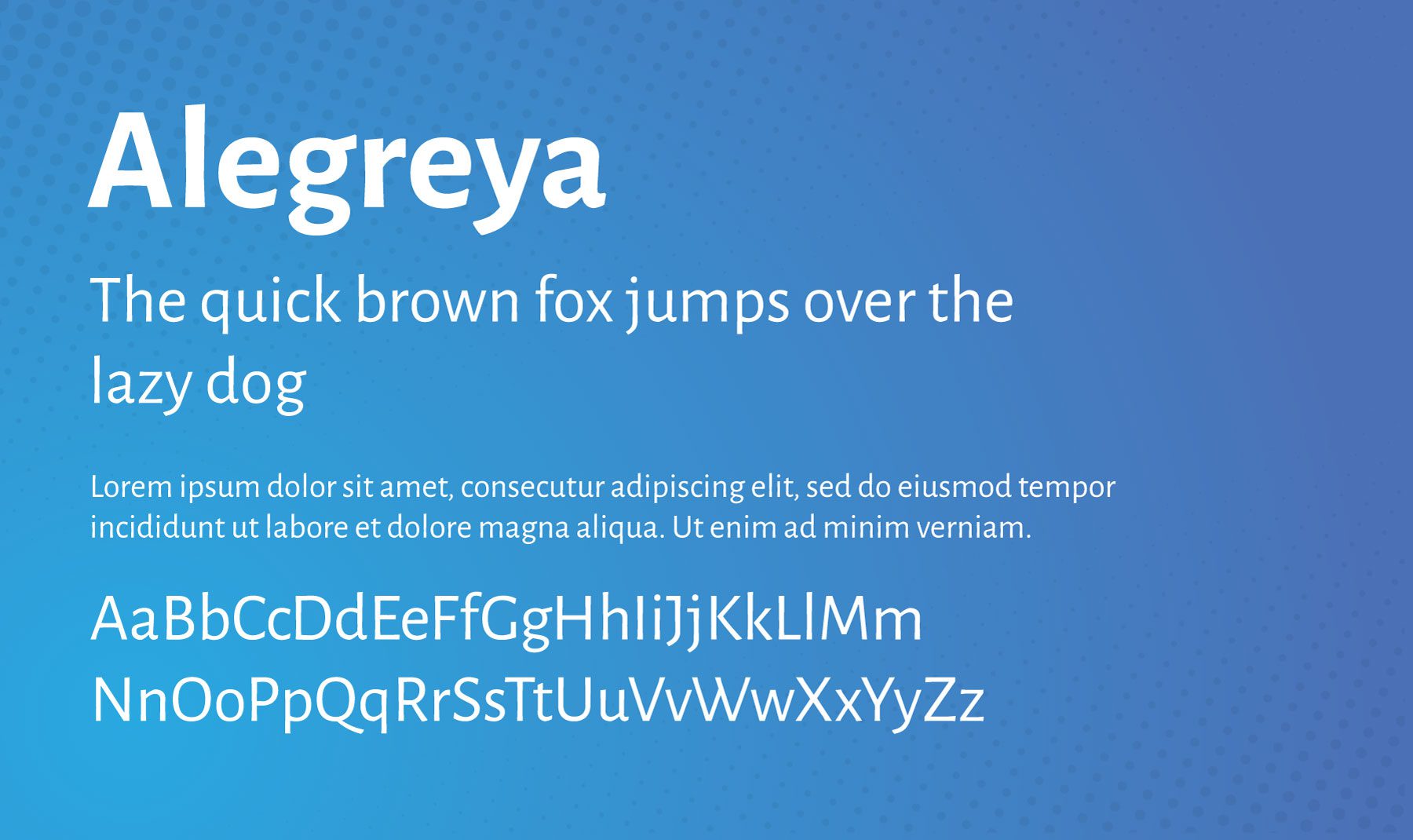
Alegreya Sans เป็นแบบอักษรซานเซอริฟที่ออกแบบโดย Juan Pablo del Peral สำหรับ Huerta Tipografica โรงหล่อชาวสเปน มีบุคลิกที่เป็นมิตร ผ่อนคลาย และเข้าถึงได้ ทำให้เหมาะสำหรับโครงการออกแบบเว็บไซต์ด้วยเสียงของแบรนด์ที่นุ่มนวล ตระกูลฟอนต์ประกอบด้วยน้ำหนัก 8 แบบตั้งแต่แบบบางจนถึงสีดำ ซึ่งแต่ละแบบมีตัวพิมพ์ใหญ่และตัวเอียงขนาดเล็ก
เหมาะสำหรับ: บล็อกโพสต์ หน้า Landing Page และเนื้อหาเว็บแบบยาวที่ต้องการความรู้สึกนุ่มนวลและอ่านง่าย
ใช้ร่วมกับ: Eczar, Open Sans, Lato, Merriweather, Source Sans 3 และ Gowun Batang
2. โดยเร็วที่สุด
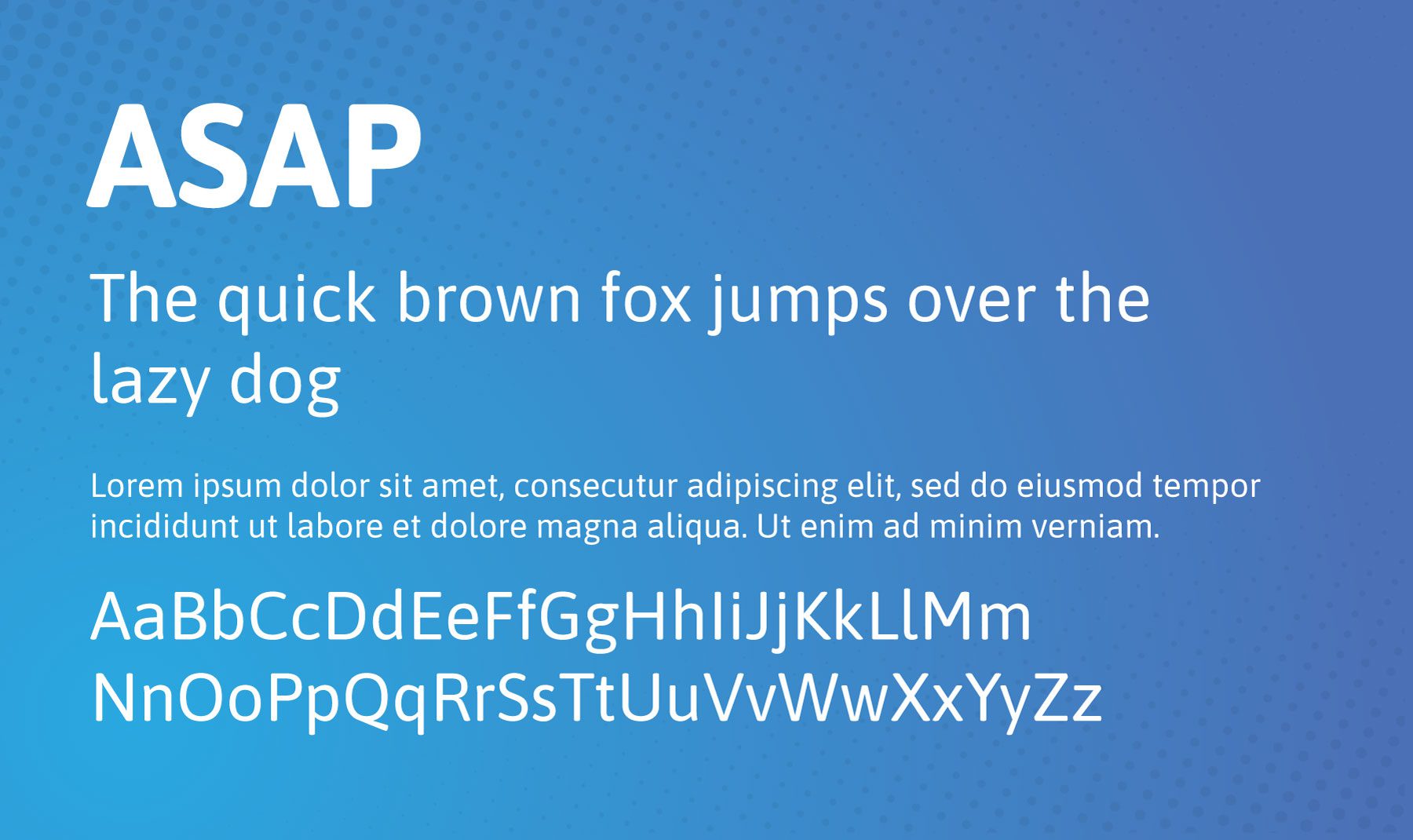
ASAP เป็นแบบอักษรซานเซอริฟสมัยใหม่ที่ออกแบบโดย Dušan Jelesijevic สไตล์เรียบง่ายสะอาดตาทำให้เหมาะสำหรับเว็บไซต์ที่ต้องการถ่ายทอดเสียงของแบรนด์ร่วมสมัยแต่เหนือกาลเวลา ตระกูลฟอนต์ประกอบด้วยน้ำหนัก 8 แบบตั้งแต่แบบบางจนถึงสีดำ ซึ่งแต่ละแบบมีตัวพิมพ์ใหญ่และตัวเอียงขนาดเล็ก
เหมาะสำหรับ: ทั้งส่วนหัวและข้อความเนื้อหา เนื่องจากรูปลักษณ์ที่สะอาดตาและทันสมัย จึงมีประสิทธิภาพโดยเฉพาะในการออกแบบเว็บไซต์ที่เกี่ยวข้องกับเทคโนโลยีและร่วมสมัย
ใช้ร่วมกับ: ฟลาเมงโก
3. ขม
Bitter เป็นแบบอักษรเซอริฟที่ออกแบบโดย Sol Matas สำหรับ Huerta Tipografica มันมีความรู้สึกหรูหราและคลาสสิกพร้อมกลิ่นอายเล็กน้อย ทำให้เหมาะสำหรับเว็บไซต์ที่ต้องการรักษาเสียงของแบรนด์ที่ซับซ้อนแต่เข้าถึงได้ ตระกูลแบบอักษรประกอบด้วยน้ำหนัก 8 แบบตั้งแต่ UltraLight ไปจนถึง Black ซึ่งแต่ละชุดประกอบด้วยตัวพิมพ์ใหญ่และตัวเอียงขนาดเล็ก
เหมาะสำหรับ: ข้อความเนื้อหา สามารถใช้กับส่วนหัวได้เช่นกัน แต่จะโดดเด่นมากเมื่อใช้กับโพสต์บนบล็อกหรือสำเนาหน้า
ใช้ร่วมกับ: Duru Sans, Montserrat, Arimo, Raleway, Roboto, Rubik, PT Sans
4. ฟิร่า แซนส์
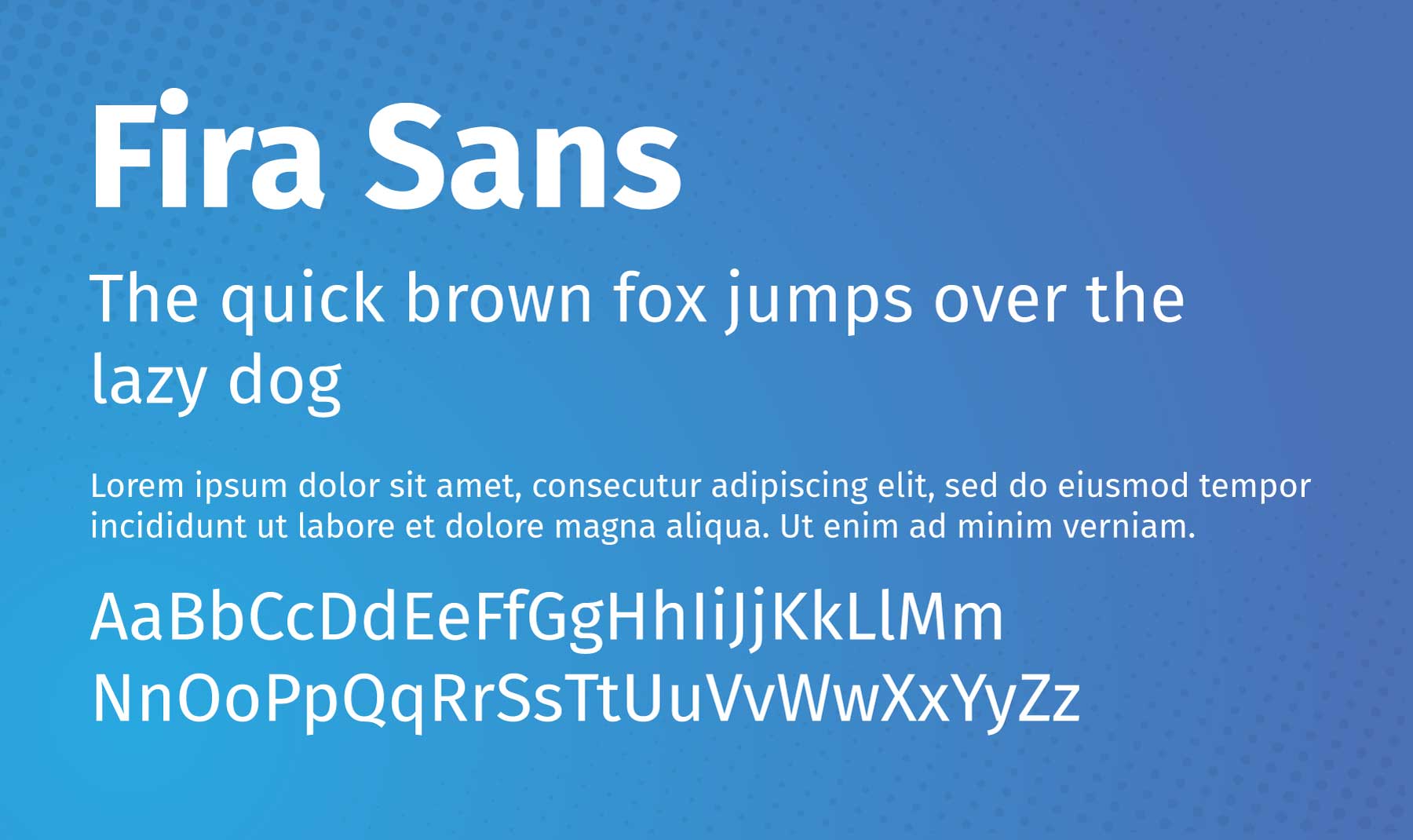
Fira Sans เป็นแบบอักษรซานเซอริฟที่ออกแบบโดย Erik Spiekermann, Ralph du Carrois, Anja Meiners และ Botio Nikoltchev จาก Carrois Type Design เริ่มแรกสร้างขึ้นสำหรับ FirefoxOS ของ Mozilla และมีเป้าหมายเพื่อให้อ่านได้บนอุปกรณ์ต่างๆ
เหมาะสำหรับ: ทั้งส่วนหัวหรือข้อความเนื้อหา เนื่องจากรูปลักษณ์ที่สะอาดตาและทันสมัย จึงมีประสิทธิภาพเป็นพิเศษบนเว็บไซต์ที่เกี่ยวข้องกับเทคโนโลยี แต่อย่าปล่อยให้สิ่งนั้นขัดขวางคุณไม่ให้ลองใช้เว็บไซต์ประเภทต่างๆ โดยเฉพาะอย่างยิ่งเนื่องจากมันจับคู่กับฟอนต์ Divi อื่น ๆ มากมายได้เป็นอย่างดี
ใช้ร่วมกับ: Inconsolata, Playfair Display, Montserrat, Lato, Source Sans 3 และ Merriweather
5. ไอบีเอ็ม เพล็กซ์ โมโน
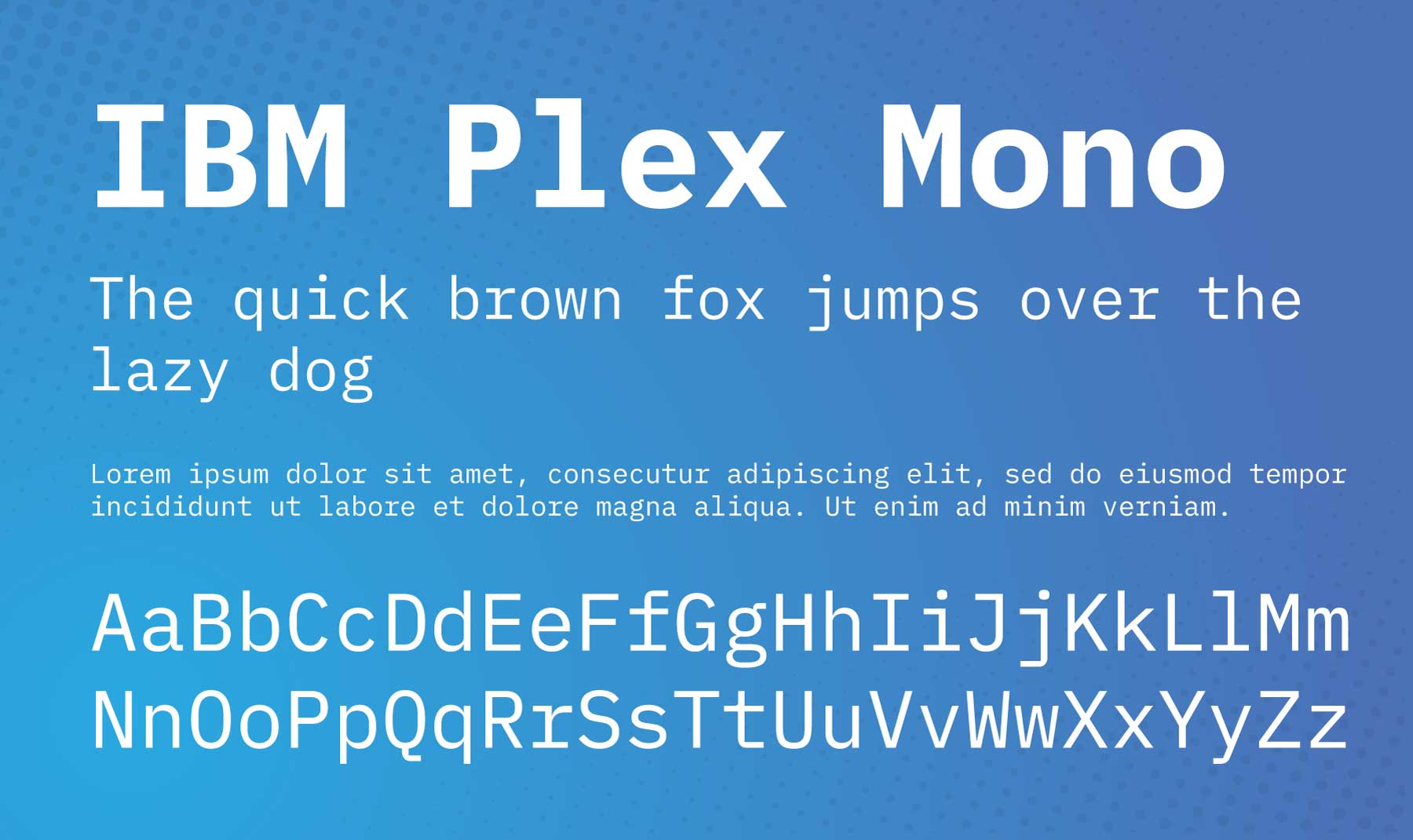
IBM Plex Mono เป็นแบบอักษรโมโนสเปซและเป็นส่วนหนึ่งของตระกูล IBM Plex ซึ่งได้รับการออกแบบมาเพื่อรวบรวมจิตวิญญาณและประวัติศาสตร์ของแบรนด์ของ IBM กลุ่มแบบอักษรถูกสร้างขึ้นโดย Mike Abbink และ Bold Monday และเปิดตัวในปี 2017 รูปแบบ Mono ได้รับแรงบันดาลใจจากเครื่องพิมพ์ดีด IBM Selectric
เหมาะสำหรับ: ส่วนหัว ข้อความเนื้อหา และข้อมูลโค้ด เนื่องจากธรรมชาติของตัวละครแต่ละตัวมีพื้นที่เท่ากัน จึงง่ายต่อการอ่านและทำความเข้าใจบนหน้าจอ ทั้งหมดนี้ทำให้มันสมบูรณ์แบบสำหรับการโพสต์บนบล็อก หากคุณมีธีมแนวย้อนยุค ก็ยิ่งดีเข้าไปใหญ่!
ใช้ร่วมกับ: Roboto, Oswald และ Playfair Display
6. อินเตอร์
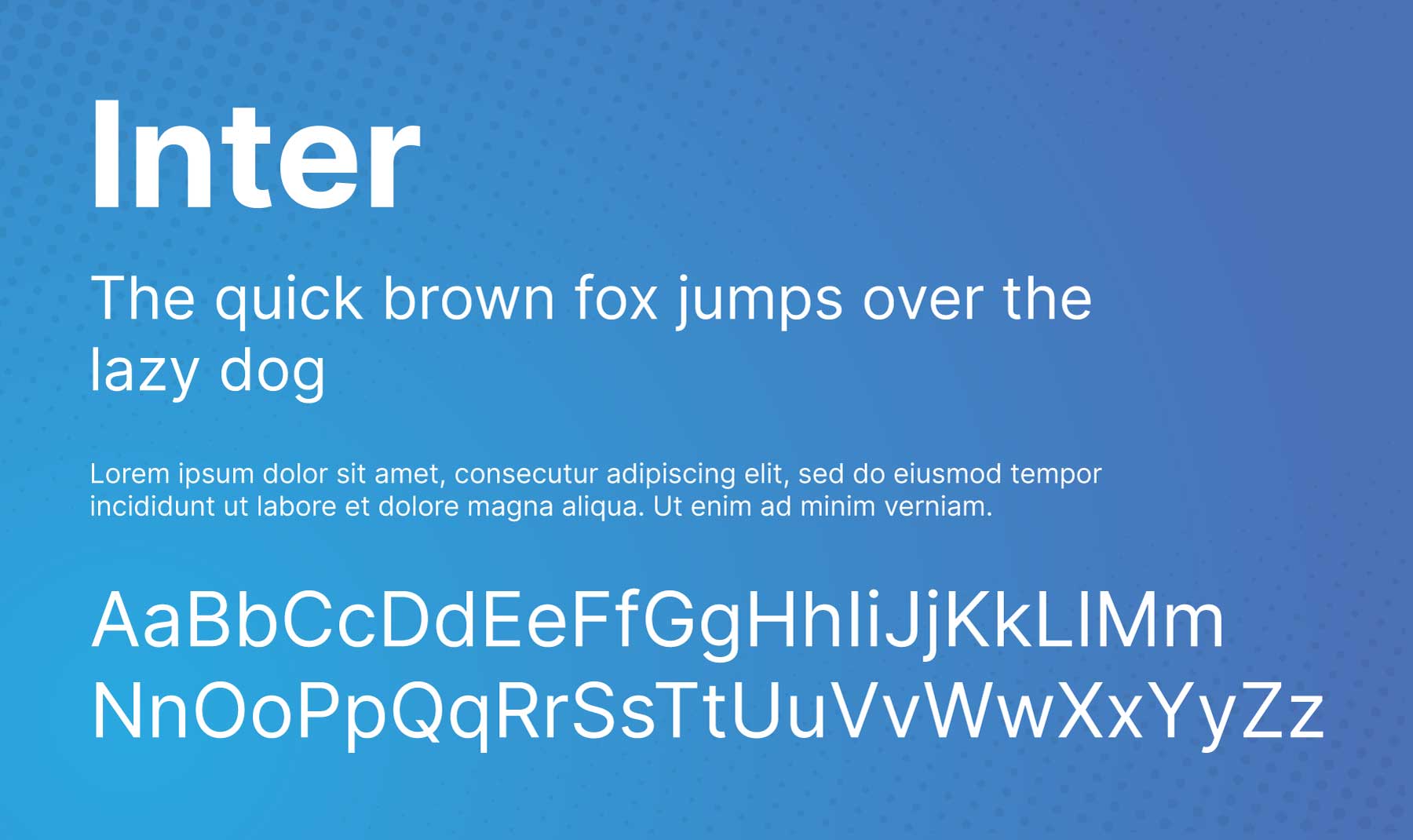
Inter เป็นแบบอักษรซานเซอริฟอเนกประสงค์ที่ออกแบบโดย Rasmus Andersson ได้รับการปรับให้เหมาะสมเพื่อให้อ่านง่ายในส่วนติดต่อผู้ใช้ ทำให้เป็นตัวเลือกยอดนิยมสำหรับการออกแบบดิจิทัล คุณสมบัติที่โดดเด่นประการหนึ่งคือความสูง x ขนาดใหญ่ ซึ่งช่วยเพิ่มความชัดเจนในขนาดที่เล็ก นอกจากนี้ยังรองรับภาษาและสคริปต์ที่หลากหลาย รวมถึงละติน กรีก และซีริลลิก
เหมาะสำหรับ: องค์ประกอบการออกแบบส่วนต่อประสานกับผู้ใช้ ใช้แบบอักษรนี้สำหรับเมนู ข้อความเมตา เบรดครัมบ์ CTA และอื่นๆ ลองจับคู่กับแบบอักษรด้านล่างเพื่อดูว่าแบบอักษรใดเหมาะกับคุณที่สุด
ใช้ร่วมกับ: Domine, IBM Plex Serif, Source Sans 3, Ovo, Rosarivo, Work Sans และ Favorite
7. คณิต
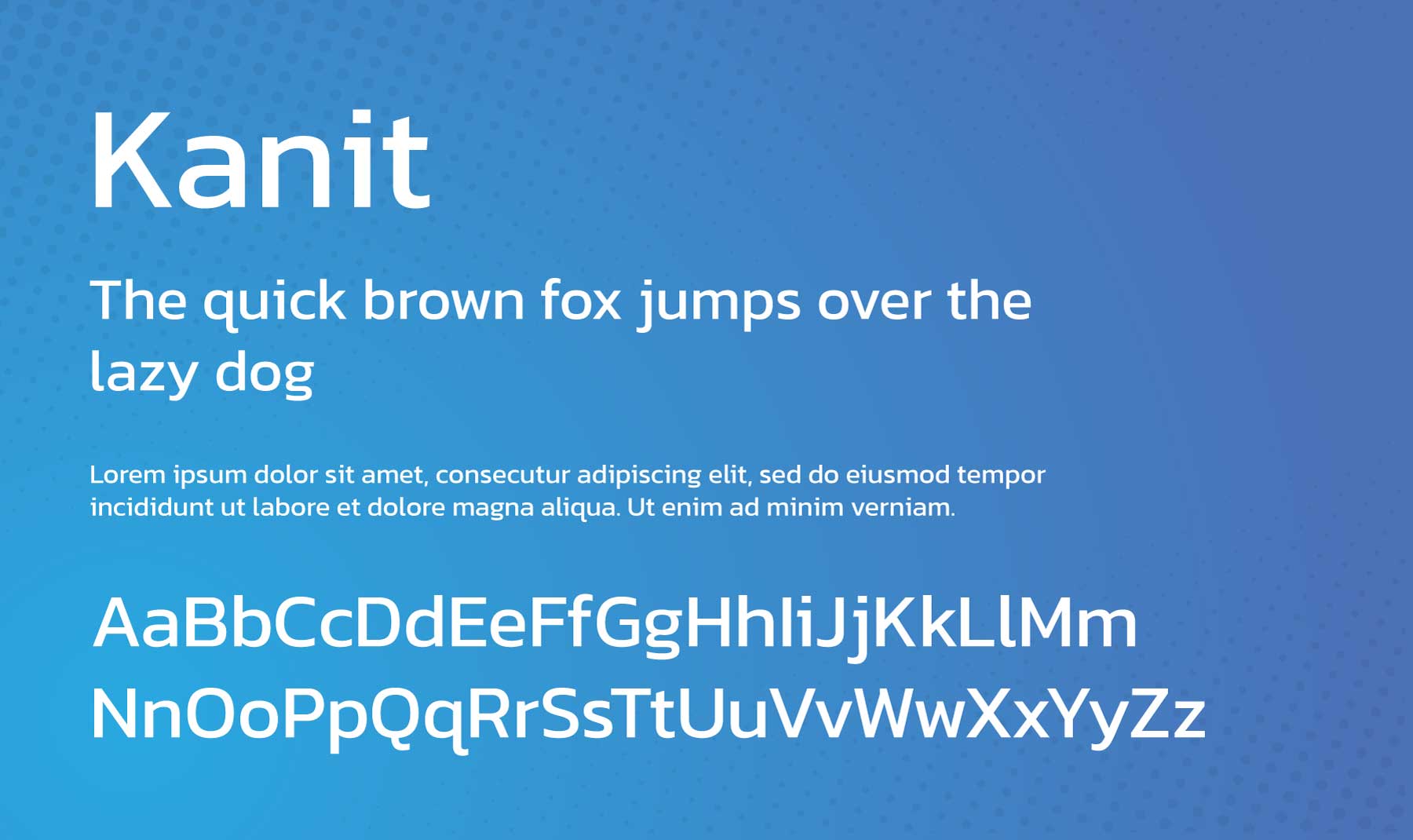
กนิษฐ์เป็นแบบอักษรซานเซอริฟที่ออกแบบโดย Cadson Demak ซึ่งเป็นโรงหล่อแบบไทย ชื่อคณิต แปลว่า คณิตศาสตร์ ในภาษาไทย ซึ่งบ่งบอกถึงพื้นฐานการออกแบบทางเรขาคณิต เป็นแบบอักษรสมัยใหม่ที่ดูล้ำสมัยพร้อมบุคลิกที่เป็นเอกลักษณ์ โดยมีมุมโค้งมนและการเว้นวรรคตัวอักษรแบบกึ่งกว้าง รองรับสคริปต์ละตินและไทย ทำให้เป็นตัวเลือกที่ยอดเยี่ยมสำหรับสภาพแวดล้อมหลายภาษา
เหมาะสำหรับ: ข่าวสาร วิทยาศาสตร์ การรักษาความปลอดภัย และแบรนด์ประเภทอื่นๆ ที่เน้นความจริงจังมากกว่าไม่เป็นทางการ เหมาะสำหรับทั้งพาดหัวและข้อความเนื้อหา
ใช้ร่วมกับ: Hind, Montserrat, Maitree, Archivo
8. ลีเบอร์ แฟรงคลิน
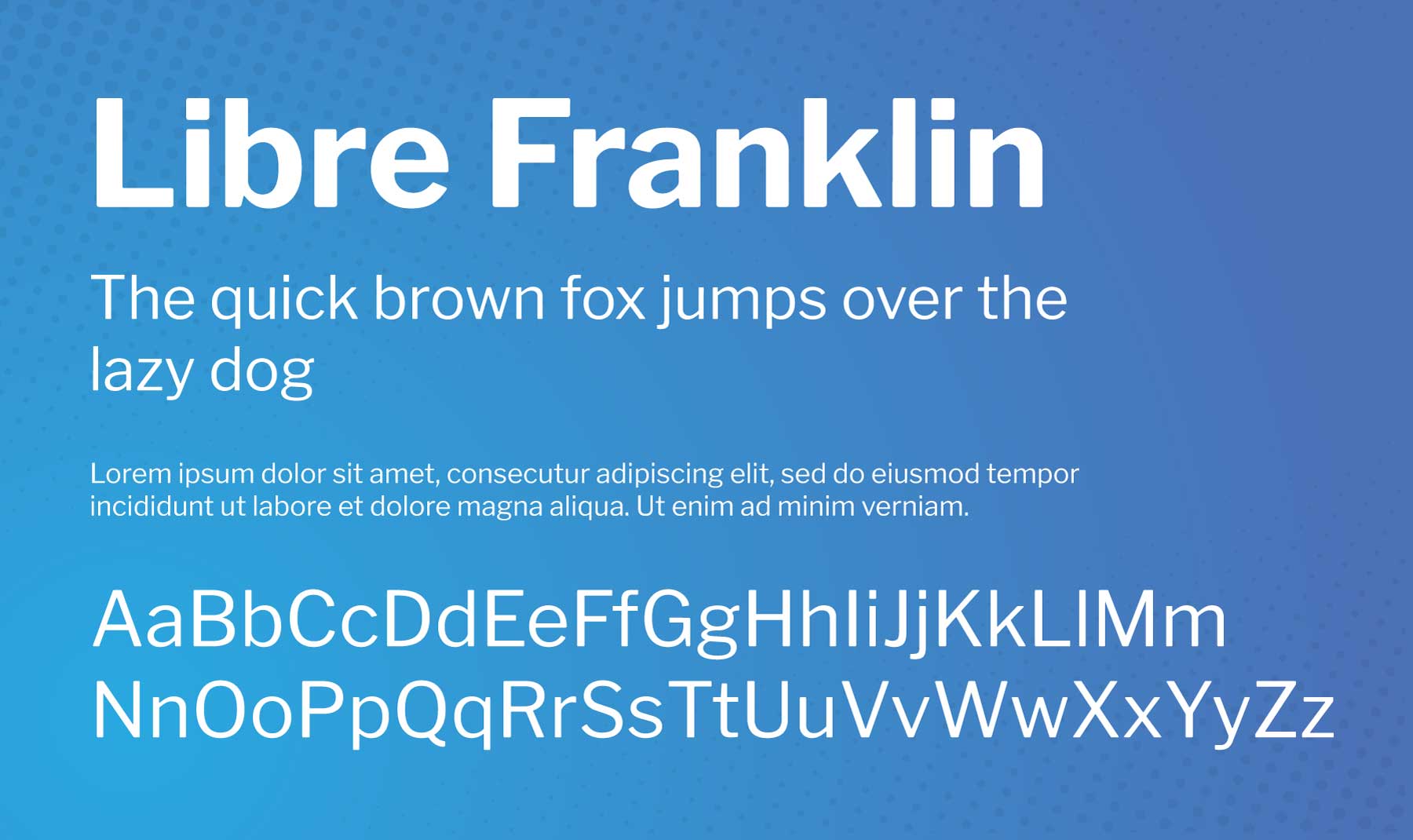
Libre Franklin เป็นการตีความใหม่และการขยายแบบอักษรคลาสสิกปี 1912 โดย Morris Fuller Benton, Franklin Gothic โครงการนี้นำโดย Impallari Type โดยมีเป้าหมายเพื่อสร้างทางเลือกโอเพ่นซอร์ส Libre Franklin เป็นฟอนต์ sans-serif ที่เป็นมิตร ซึ่งรองรับโครงการสร้างแบรนด์และการออกแบบเว็บไซต์ที่ซับซ้อน ทำให้เหมาะสำหรับการใช้งานเทคโนโลยีและสมัยใหม่
เหมาะสำหรับ: อินเทอร์เฟซดิจิทัล ข้อความ และส่วนหัวเนื่องจากมีรูปลักษณ์ที่เป็นกลางและชัดเจน น้ำหนักที่หลากหลายของแบบอักษรยังให้ความยืดหยุ่นอย่างมากเมื่อสร้างลำดับชั้นภาพในการออกแบบของคุณ ทำให้เป็นฟอนต์ที่ดีสำหรับเนื้อหาที่มีโครงสร้าง เช่น โพสต์ในบล็อก
ใช้ร่วมกับ: Neuton, Libre Baskerville, Public Sans
9. ผู้ประกาศข่าว
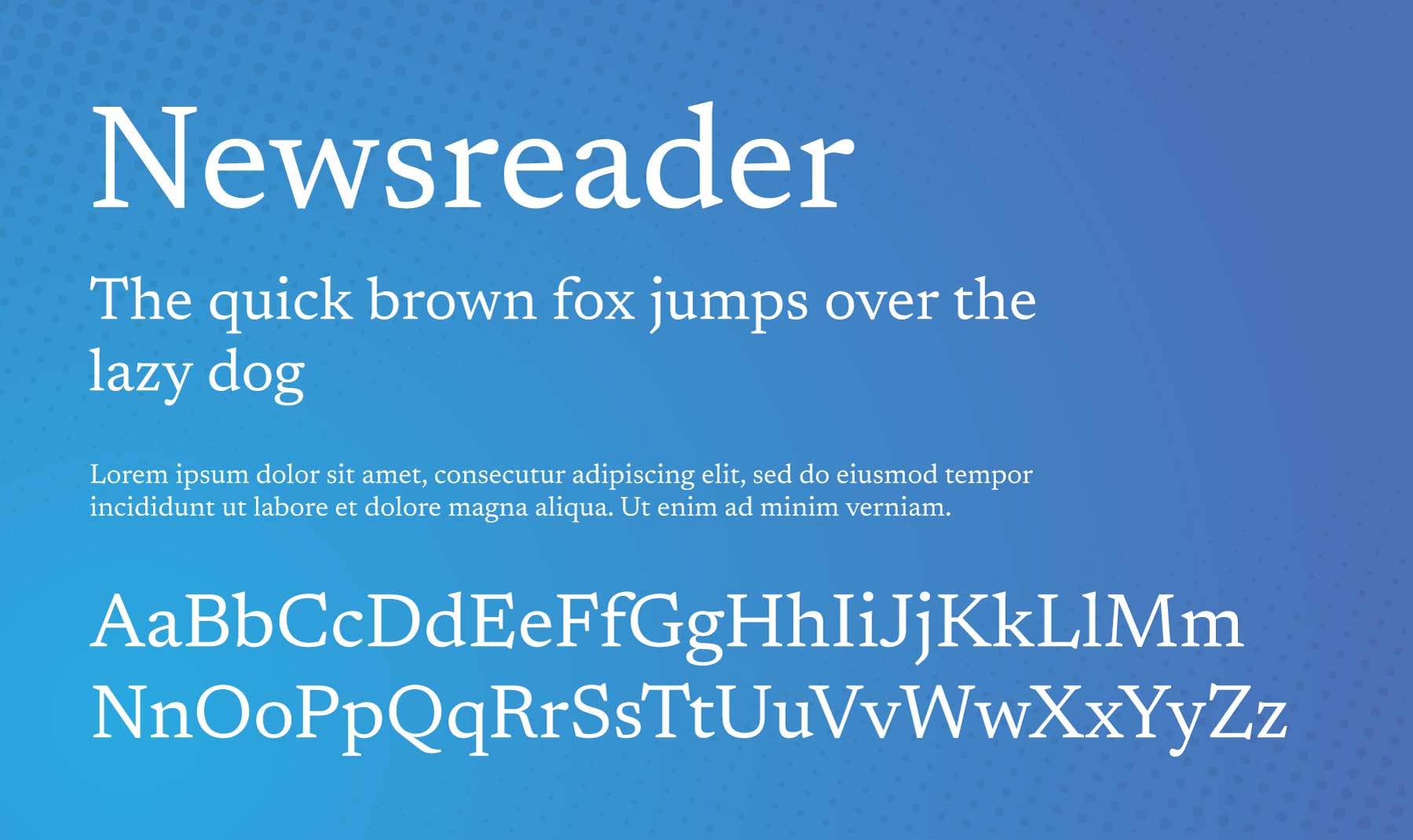
Newsreader เป็นแบบอักษร serif ที่เป็นเอกลักษณ์ซึ่งออกแบบตามประเภทการผลิต Google Fonts กำหนดให้ใช้เพื่อการอ่านบนหน้าจออย่างต่อเนื่องในสภาพแวดล้อมที่มีเนื้อหามากมาย เช่น เว็บไซต์ข่าว โปรแกรมอ่านข่าวมีความหลากหลายสูงและมาในรูปแบบต่างๆ ตั้งแต่แสงพิเศษไปจนถึงตัวหนาเป็นพิเศษ มีไว้สำหรับการอ่านในรูปแบบยาวเป็นหลัก ทำให้เป็นตัวเลือกที่ยอดเยี่ยมสำหรับบล็อก บทความ และหนังสือดิจิทัล
เหมาะสำหรับ: โพสต์ในบล็อกที่มีรูปแบบยาว กรณีศึกษา รายงาน หรืออะไรก็ตามที่ต้องอ่านเยอะๆ
ใช้ร่วมกับ: อาริโม
10. โนโตะเซริฟ
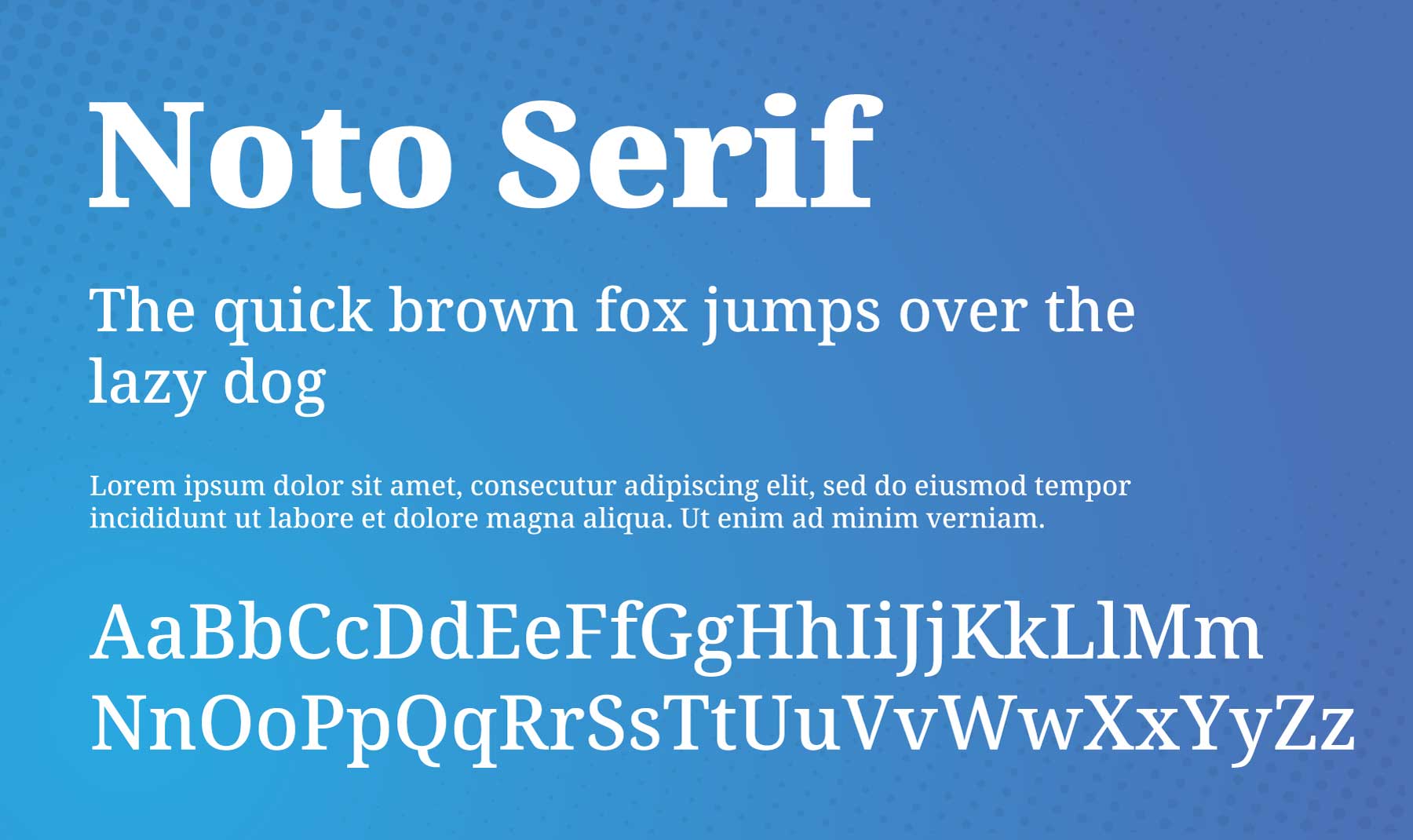
Noto Serif เป็นตระกูลแบบอักษรอเนกประสงค์และครอบคลุมที่พัฒนาโดย Google ฟอนต์เซอริฟแบบมอดูเลตนี้ (หมายถึงความหนาของเส้นขีดจะแตกต่างกันไปในแต่ละอักขระ) รองรับสคริปต์ละติน ซีริลลิก และกรีก ทำให้เหมาะสำหรับภาษาและแอปพลิเคชันต่างๆ Noto Serif มีชื่อเสียงในด้านความสามารถในการปรับตัว โดยให้ระบบการพิมพ์ที่กลมกลืนกัน
เหมาะสำหรับ: ข้อความเนื้อหาและพาดหัวข่าวทำให้อ่านง่ายและมีความสวยงาม หากคุณมีเว็บไซต์หลายภาษาที่มีผู้ชมที่พูดภาษากรีกหรือซีริลลิกได้ นี่เป็นตัวเลือกที่ดี
ใช้ร่วมกับ: Noto Sans JP, Open Sans, Source Sans 3, Bebas Neue, Lato และ Oswald
11. นูนิโต
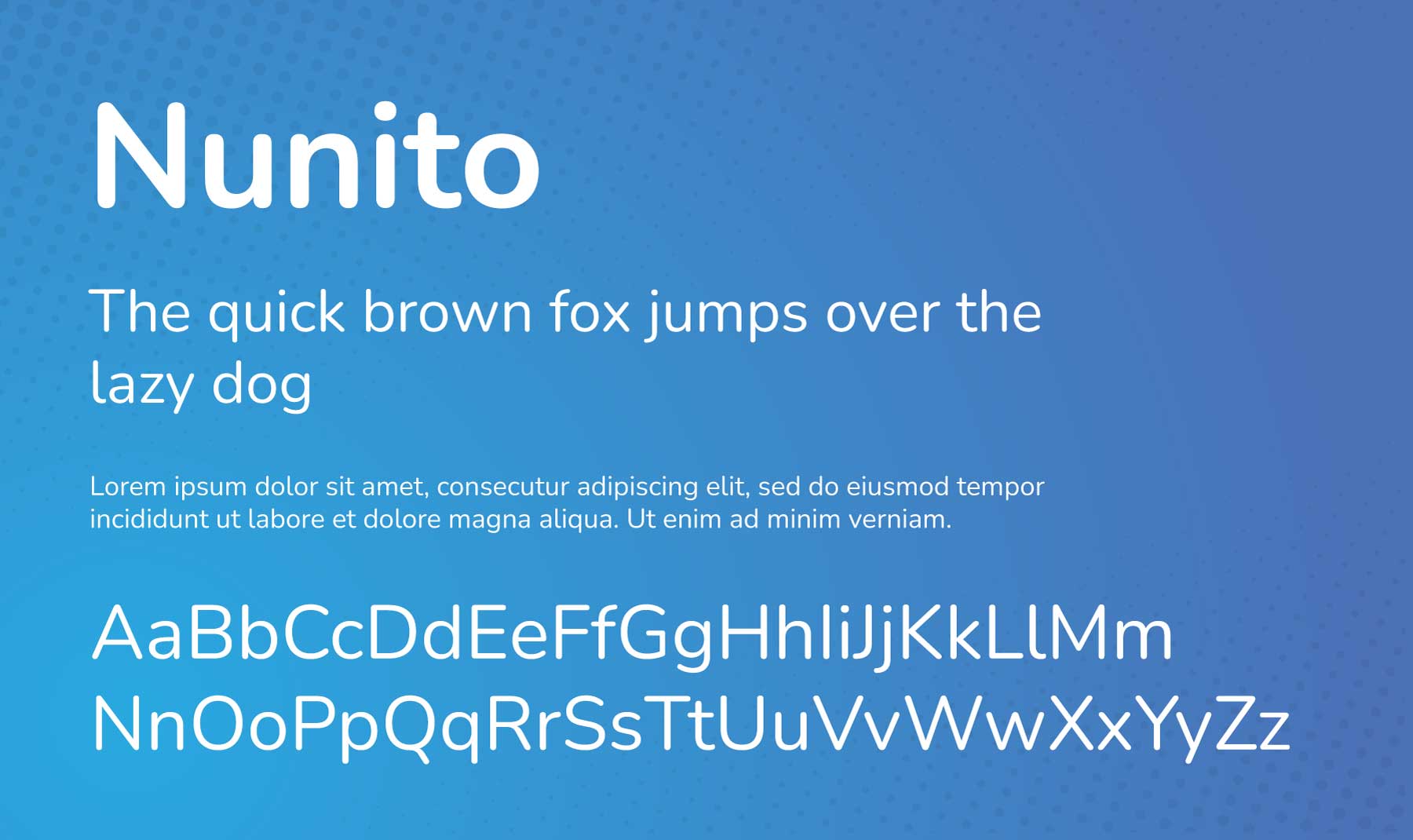
Nunito เป็นตระกูลแบบอักษร sans-serif ที่มีความสมดุล สร้างสรรค์โดย Vernon Adams มีการออกแบบขั้วต่อแบบโค้งมน และขึ้นชื่อในเรื่องความกว้างของเส้นที่บางและสม่ำเสมอ ทำให้สามารถอ่านได้ง่ายและเหมาะสำหรับทั้งตัวเครื่องและสำเนาจอแสดงผล
เหมาะสำหรับ: ข้อความที่แสดงและส่วนหัว เช่น คำพูด บทวิจารณ์ หรือคำโปรยบนแลนดิ้งเพจ นอกจากนี้ยังเหมาะสำหรับเว็บไซต์พอร์ตโฟลิโอการออกแบบ การเงิน การพัฒนา และเอเจนซี่อีกด้วย
ใช้ร่วมกับ: อาซูล, โดมิเน, เทโค, แวมไพร์วัน, มอนต์เซอร์รัต, มาร์เซลลัส, ออสวอลด์
12. พีที แซนส์
PT Sans เป็นแบบอักษรซานเซอริฟสากลที่ออกแบบโดย Alexandra Korolkova, Olga Umpeleva และ Vladimir Yefimov เปิดตัวโดย ParaType ในปี 2009 ได้รับการพัฒนาโดยเป็นส่วนหนึ่งของโครงการ "ประเภทสาธารณะของสหพันธรัฐรัสเซีย" PT Sans มีประโยชน์ในหลายแอปพลิเคชัน ตั้งแต่เว็บไปจนถึงการพิมพ์ เนื่องจากมีความสามารถในการอ่านสูงและการออกแบบที่สะอาดตา
เหมาะสำหรับ: สื่อการอ่านที่มีเนื้อหายาว เช่น บล็อกโพสต์ กรณีศึกษา หรือรายงาน น้ำหนักที่หลากหลายยังให้ความยืดหยุ่นเมื่อสร้างลำดับชั้นภาพในการออกแบบเว็บไซต์ของคุณ
ใช้ร่วมกับ: Rubik, Playfair Display, Lato, Inconsolata, Poppins, Tenor Sans, IBM Plex, Vollkorn SC และ Nunito
13. แบบสอบถาม
Questrial เป็นแบบอักษรซานเซอริฟที่ออกแบบโดย Joe Prince นำเสนอสไตล์ทันสมัยที่เสริมด้วยลักษณะเฉพาะของแบบอักษรคลาสสิก Questrial มีรูปแบบตัวอักษรที่ค่อนข้างสั้นและขยายออกไป ซึ่งมีประโยชน์ในบริบทการออกแบบที่หลากหลาย
เหมาะสำหรับ: ข้อความและส่วนหัวของโพสต์หรือหน้า ความสวยงามที่สะอาดตาและเป็นกลางทำให้เหมาะสำหรับโปรเจ็กต์การออกแบบเว็บไซต์ที่ต้องการสื่อถึงความสง่างาม มีระดับ และความแปลกใหม่ (แค่ดู "Q" ที่ขี้เล่นหลอกลวงนั้น!)
ใช้ร่วมกับ: ควอตโตรเซนโต
14. เรียกซ้ำ
Recursive เป็นแบบอักษรอเนกประสงค์ที่มีเอกลักษณ์เฉพาะตัวที่สร้างขึ้นโดย Arrow Type โดยนำเสนอสไตล์ที่กำหนดไว้ล่วงหน้าที่หลากหลาย โดยได้รับแรงบันดาลใจจากจังหวะสบายๆ จังหวะเดียว ซึ่งเป็นสไตล์การเขียนพู่กันที่ใช้ในการลงสีป้าย แต่ได้รับการออกแบบมาเพื่อตอบสนองความต้องการของหน้าจอดิจิทัลเป็นหลัก
เหมาะสำหรับ: องค์ประกอบการออกแบบอินเทอร์เฟซผู้ใช้ ข้อความที่แสดง ส่วนย่อยโค้ด อินโฟกราฟิก และส่วนหัว ตัวอย่างอาจรวมถึงเมนู การแสดงเส้นทาง ข้อมูลโค้ดในบล็อกโพสต์ กรณีศึกษา บทวิจารณ์จากลูกค้า และอื่นๆ
ใช้ร่วมกับ: Nunito, Rubik และ IBM Plex Sans
15. โวลกรณ์
Vollkorn เป็นแบบอักษรเซอริฟที่ออกแบบโดย Friedrich Althausen เป็นหนึ่งในแบบอักษรแรกสุดที่ถูกรวมไว้ใน Google Fonts ในปี 2010 Vollkorn ซึ่งแปลว่า "ทั้งเมล็ด" ในภาษาเยอรมัน มีจุดมุ่งหมายให้เป็นแบบอักษรที่เงียบ เรียบง่าย และใช้งานได้ดีสำหรับการใช้งานในวงกว้าง
เหมาะสำหรับ: ข้อความพาดหัว คำบรรยาย และ CTA เป็นฟอนต์ที่ทำได้ทุกอย่าง ลักษณะที่ละเอียดอ่อนทำให้เป็นตัวเลือกที่ยอดเยี่ยมเมื่อคุณต้องการแบบอักษรที่สามารถอ่านได้และใช้งานได้จริง แต่ยังคงเสริมบุคลิกให้กับเว็บไซต์ของคุณ
ใช้ร่วมกับ: PT Sans, Poppins, Lato, Montserrat, Source Sans 3
คำกล่าวยกย่อง
เมื่อต้องจัดการกับแบบอักษรนับร้อยแบบ การพิจารณาแบบอักษรที่ "ดีที่สุด" อาจเป็นเรื่องยาก แบบอักษรด้านล่างสร้างรายชื่อผู้เข้ารอบสุดท้ายของโพสต์นี้ หากคุณไม่พบแบบอักษรที่ต้องการด้านบน แบบอักษรเหล่านี้ก็คุ้มค่าที่จะลองดู
- อาริโม
- ไม่ปลอบใจ
- โรซาริโอ
- ซิกนิกา
- สเปกตรัม
- อูบุนตู
เคล็ดลับและแนวทางปฏิบัติที่ดีที่สุดสำหรับการใช้แบบอักษร Divi
เมื่อเลือกแบบอักษร (หรือแบบอักษร) ของคุณแล้ว เราขอแนะนำเคล็ดลับและแนวทางปฏิบัติที่ดีที่สุดบางประการเพื่อใช้ประโยชน์สูงสุดจากแบบอักษรภายใน Divi
อัปโหลดแบบอักษรที่กำหนดเองด้วยการลากและวาง
หากคุณไม่พบแบบอักษรในตัวเลือกแบบอักษรที่หลากหลายของ Divi คุณสามารถใช้ฟังก์ชันลากและวางของ Divi เพื่ออัปโหลดแบบอักษรที่กำหนดเองของคุณได้เสมอ
สิ่งที่คุณต้องทำคือลากไฟล์ฟอนต์ OTF หรือ TTF ไปยังหน้าที่เปิดใช้งาน Divi Builder กล่องโต้ตอบจะปรากฏขึ้นโดยอัตโนมัติ พร้อมให้คุณอัปโหลดแบบอักษร มันยังช่วยให้คุณสามารถแทนที่แบบอักษรที่มีอยู่ด้วยแบบอักษรที่อัปโหลดใหม่ได้!
เพิ่มการออกแบบไล่ระดับสีข้อความด้วย Divi AI
Divi AI เปิดความเป็นไปได้ไม่รู้จบสำหรับเอฟเฟกต์การออกแบบที่กำหนดเอง ตัวอย่างเช่น คุณสามารถใช้ Divi AI เพื่อเพิ่ม CSS ที่กำหนดเองให้กับองค์ประกอบการพิมพ์ ในตัวอย่างนี้ เราใช้ Divi AI เพื่อเพิ่มการซ้อนทับแบบไล่ระดับสีให้กับส่วนหัวนี้โดยใช้ข้อความแจ้งง่ายๆ: “สร้างการซ้อนทับพื้นหลังแบบไล่ระดับสีบนส่วนหัว h1 โดยใช้สีแดงสองสีในเค้าโครงนี้”
เปิดใช้งาน Divi Builder บนหน้าใดก็ได้เพื่อทดลองใช้ด้วยตัวคุณเอง จากนั้นเลือกโมดูลข้อความที่มีส่วนหัว ไป ที่แท็บขั้นสูง > CSS แบบกำหนดเอง แล้วคลิกปุ่ม AI หลังจากนั้น ให้พิมพ์ข้อความแจ้งของคุณในกล่องโต้ตอบใหม่ และดู Divi AI ไปทำงาน
เปิดใช้งานการแคชแบบอักษรของ Google
สุดท้ายนี้ เพื่อให้แน่ใจว่าไซต์ของคุณทำงานในระดับประสิทธิภาพสูงสุด คุณจะต้องแน่ใจว่าคุณได้เปิดใช้งานการแคชแบบอักษรของ Google ในตัวเลือกธีมของ Divi โดยไปที่ ตัวเลือกธีม Divi > ทั่วไป > ประสิทธิภาพ จากนั้นตรวจสอบให้แน่ใจว่าคุณได้เปิดใช้งานการสลับข้าง "ปรับปรุงการโหลดแบบอักษรของ Google"
แบบอักษร Divi ที่ดีที่สุด: สรุปและบทสรุป
Divi มาพร้อมกับแบบอักษรมากกว่า 800 แบบ การตั้งค่าการออกแบบข้อความที่ใช้งานง่าย และเครื่องมือขั้นสูง เช่น Divi AI ที่เปิดความเป็นไปได้ในการออกแบบที่ไม่มีที่สิ้นสุด ในโพสต์นี้ เราได้กล่าวถึงแบบอักษรที่ดีที่สุดสิบห้าแบบที่มีอยู่ใน Divi และการกล่าวถึงอันทรงเกียรติบางส่วน ซึ่งทั้งหมดนี้คุ้มค่าแก่การพิจารณาสำหรับโปรเจ็กต์ต่อไปของคุณ